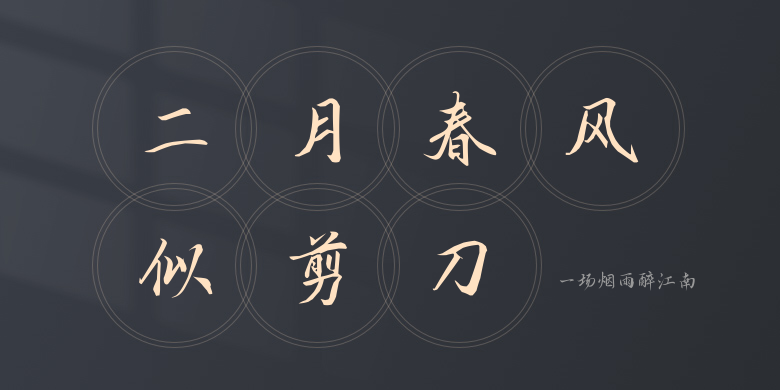
一场烟雨醉江南
一场烟雨醉江南,这款字体结构工整、笔画清晰,兼顾美观与易读性,适用于标题、正文、海报、包装、LOGO 等多种场景。字形优雅稳定,风格百搭耐看,适配日常排版与创意设计,让文字呈现更舒适、更具质感。一场烟雨醉江南一笔一画,皆是细节,以均衡的比例、流畅的线条打造舒适视觉体验,字形端正大气,风格简约现代。无论是商业设计、品牌宣传还是日常排版,都能轻松驾驭,让文字更有格调与力量。一场烟雨醉江南字体下载。